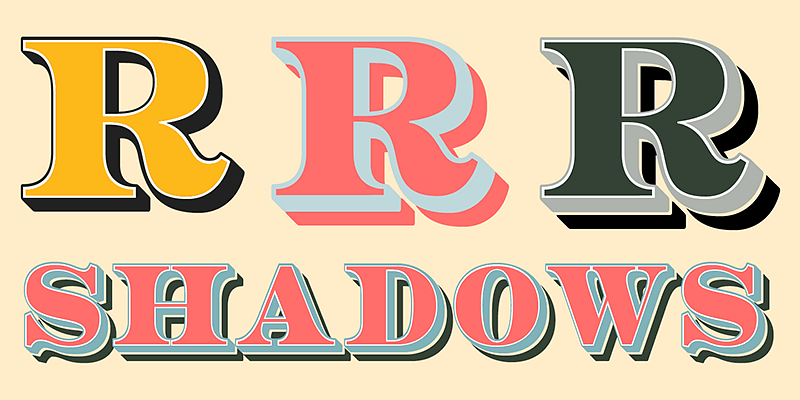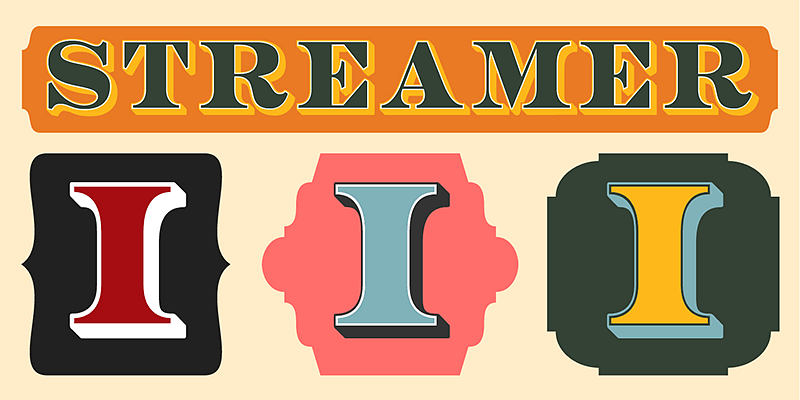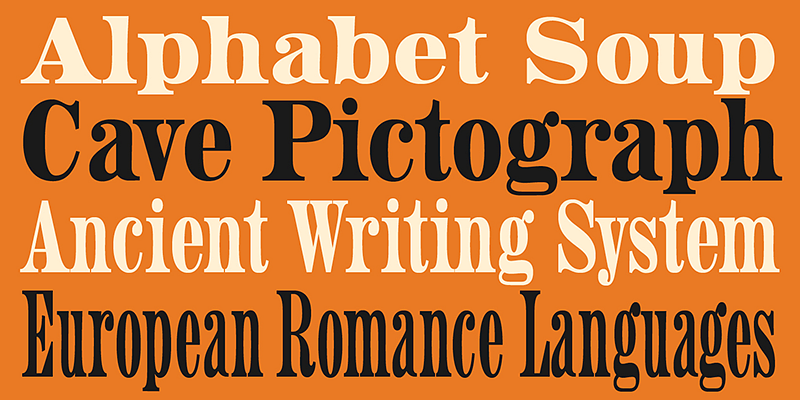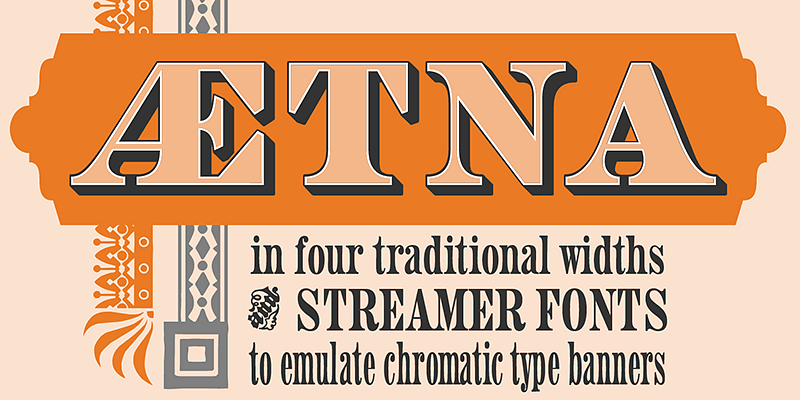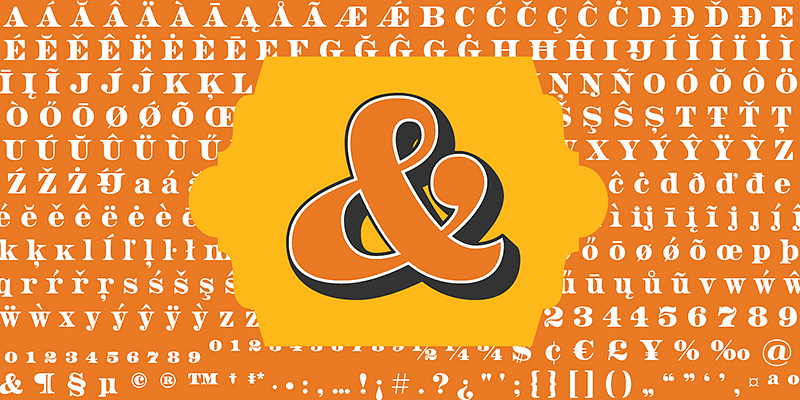
HWT Aetna est une renaissance du style romain robuste s’inspirant des caractères en bois. Cette version numérique propose quatre largeurs, ainsi que quatre versions Streamer qui permettent de créer des effets de couche chromatique.
Hamilton Wood Type Collection
Hamilton Wood Type Collection, créée en 2012, est née d’une aventure commune entre la fonderie P22 Type Foundry et le Hamilton Wood Type and Printing Museum. L’objectif initial était d’assurer la sauvegarde de toute une ère typographique en rendant les motifs classiques en bois disponibles sous forme de polices numériques pour le public d’aujourd’hui. Cette collection historique d’empattements revisités, de polices sans serif réinterprétées, d’ornements décoratifs, de réhabilitations d’écritures scriptes et de designs chromatiques originaux se révèle d’un intérêt exceptionnel et d’une utilité remarquable pour toute création axée sur l’imagination.